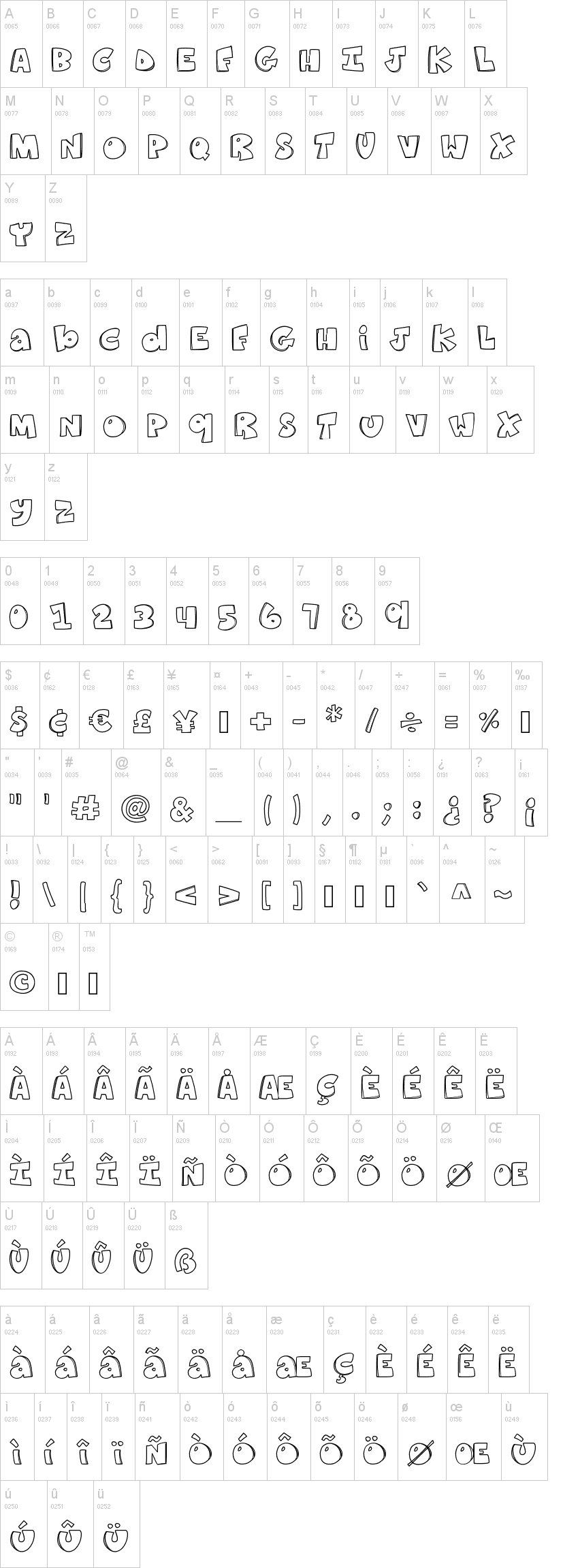
K26 Comic Kats
K26 Comic Kats是一种有趣的手写风格字体,非常适合用于漫画、卡通、游戏、海报等项目。该字体具有独特的手写风格,包含26个大写字母和数字0-9。它的设计受到早期漫画和卡通的启发,具有非常有趣的外观和良好的可读性。K26 Comic Kats的字母形状非常流畅,有很多圆弧和曲线,使得整个字体看起来非常活泼且富有表现力。这种字体适合用于为你的设计增加一些特别的风格和个性化的元素。
K26 Comic Kats是一款非常不错的手写艺术字体,具有很好的视觉感,适合于文化类的宣传设计、商业类品牌的广告和产品包装设计以及个性化文字排版等较多场景。
K26 Comic Kats字符映射图